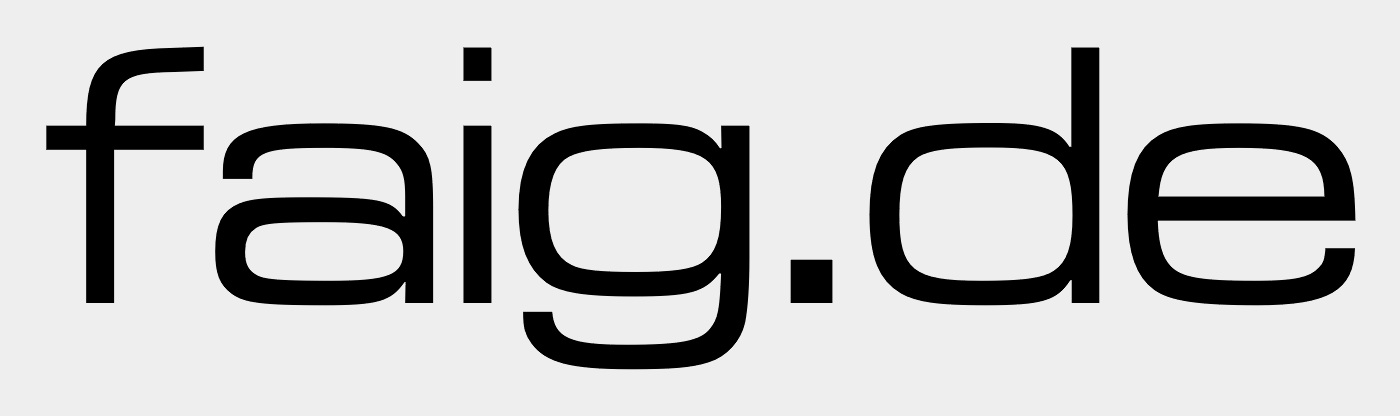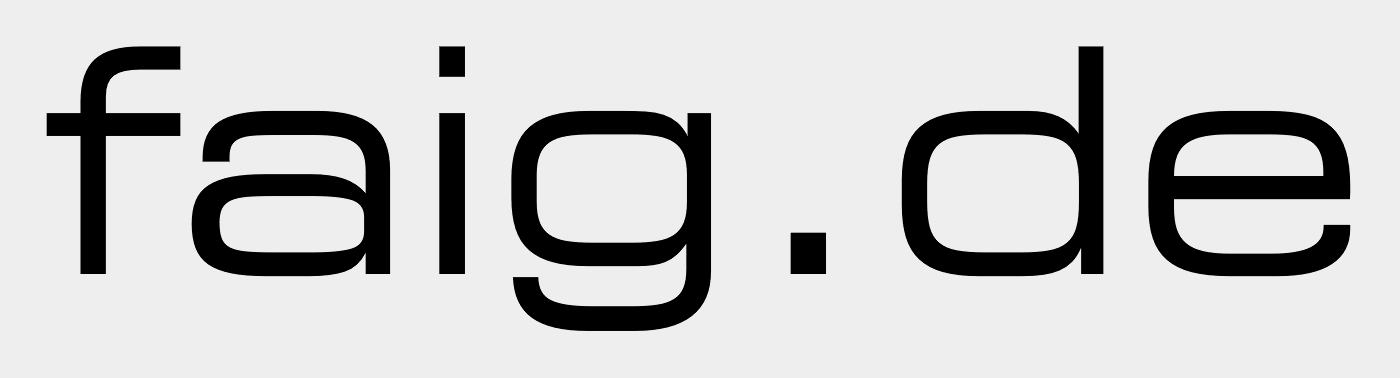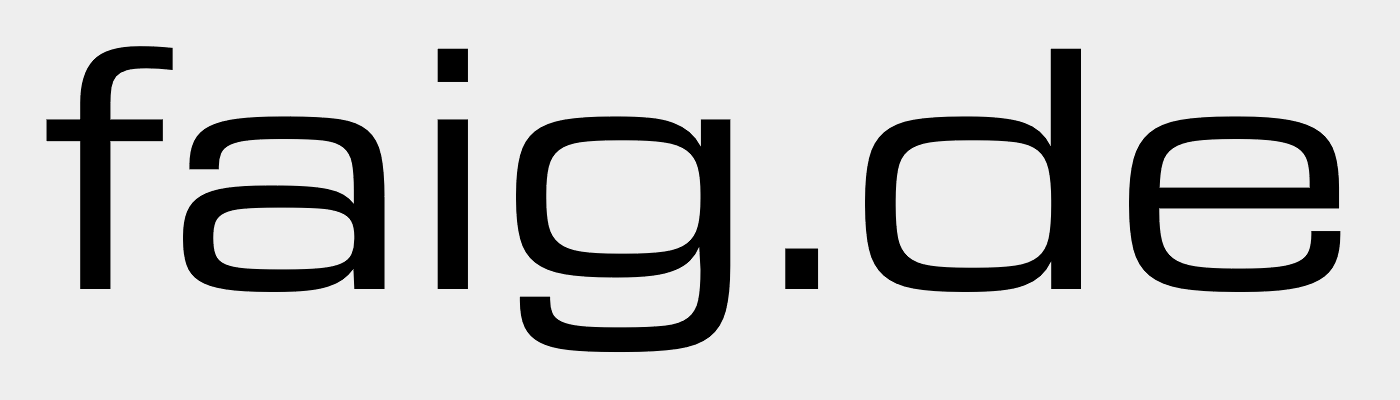
Suche Schriftart ähnlich Eurostyle (Karl Faig GmbH)
kennt jemand die Schriftart der Beispielgrafik?
Ich habe es mit Eurostyle probiert und in die Länge gezogen. Das muss man aber so stark machen, dass die Strichstärken zu unregelmäßig sind?
Kennt deshalb jemand vielleicht die gleiche Schriftart der Beispielgrafik?